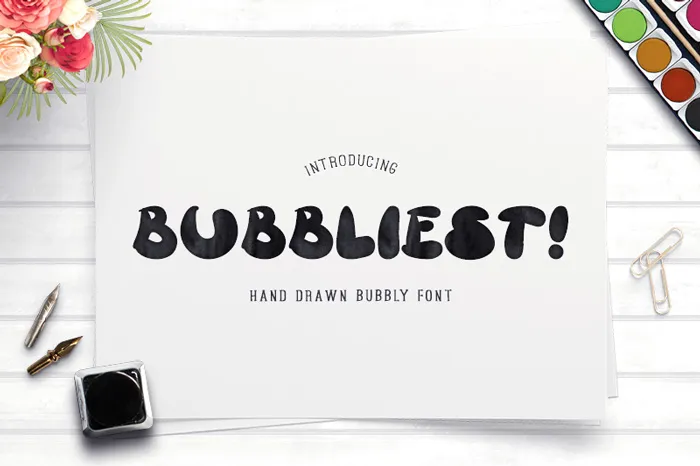
Bubbliest Font – Download Grátis
A Bubbliest Font é uma linda fonte de desenho a mão que oferece aquele toque divertido e criativo para suas criações digitais. Conhecida como o premium, agora está disponível gratuitamente no The Hungry Jpeg. Essa fonte adorável, perfeita para atividades festivas ou semelhantes, pode ser usada tanto em projetos pessoais quanto comerciais. Com sua característica de desenho a mão delicado e cítrico, ela se adapta perfeitamente para cartões de aniversário e cartas de felicitações, oferecendo um toque divertido para qualquer ocasião especial. A Bubbliest Font não apenas é uma fonte, mas também uma forma de adicionar um pouco de leveza e alegria à sua arte digital.